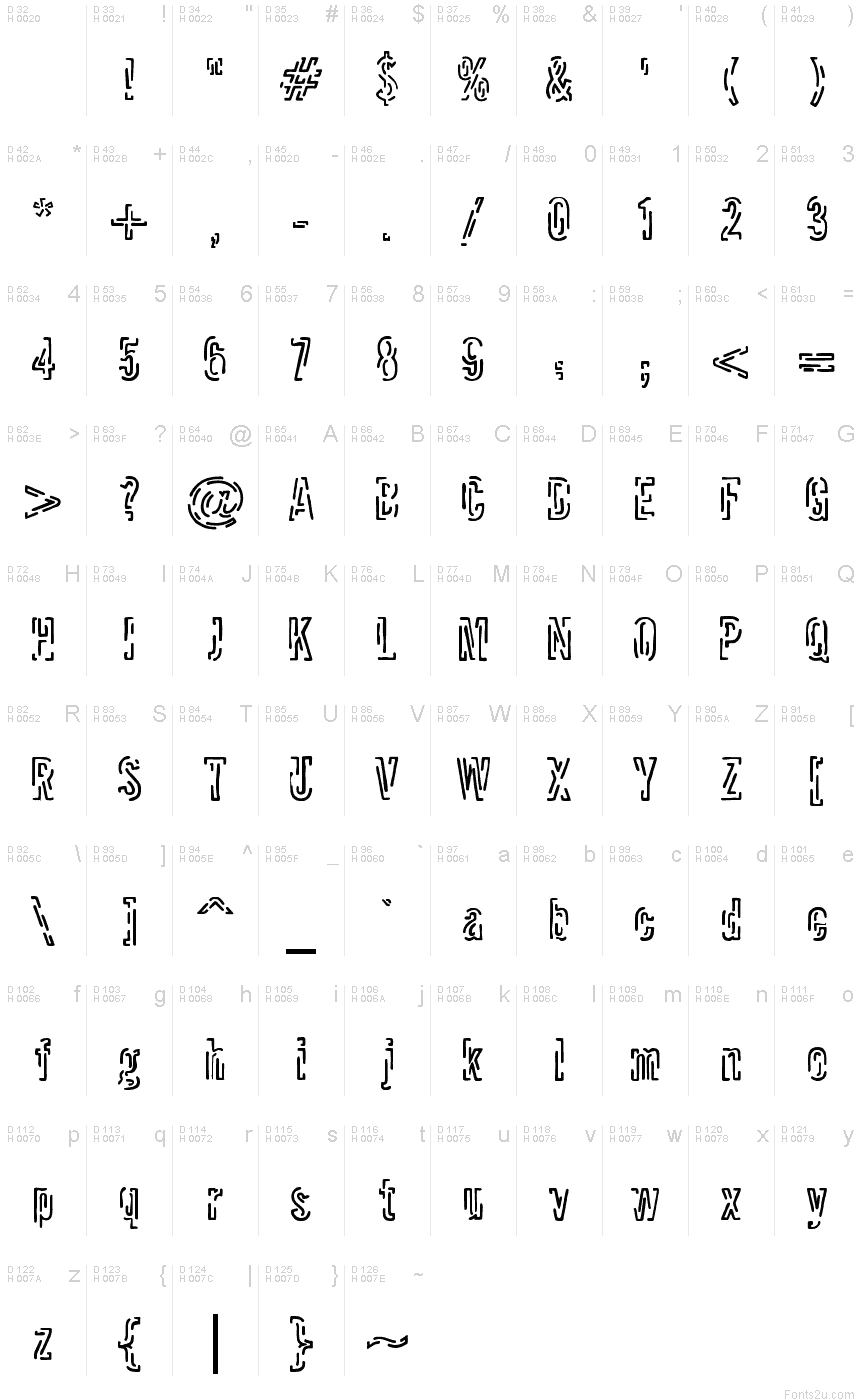
Packet
Packet od Surface Type to bezpłatny, wyświetlaczowy krój pisma o erozyjnym charakterze i zabawnym klimacie późnych lat 90. Litery łączą masywne, zaokrąglone kontury z celowymi pęknięciami i wcięciami, dzięki czemu alfabet przypomina trochę szablon, a trochę napisy z kreskówek. Całość ma dynamiczny rytm, który sprawia, że szorstkość wydaje się lekka, a nie przytłaczająca.
Packet naturalnie sprawdza się na plakatach, klubowych ulotkach, okładkach zinów, ekranach tytułowych gier czy szkicach logotypów, gdzie krótkie słowa wymagają wyrazistej, poszarpanej sylwetki. Jako darmowy font, świetnie nadaje się również do nagłówków, monogramów i powiększonych inicjałów, ponieważ otwarte kształty i wycięte łączenia sprawiają, że nawet kilka liter robi wrażenie.